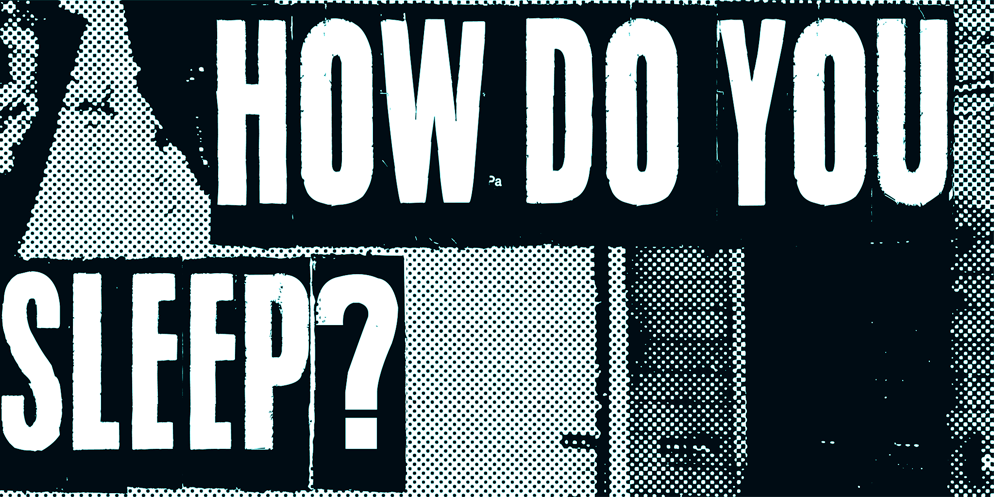
A How do you sleep? Font é uma elegante tipografia francesa para uso pessoal gratuita. Ela foi criada pelo designer Hamilton, conhecido por seus desenhos delicados e versáteis. Esta fonte tem um tom aconchegante e envolvente que se adapta perfeitamente para projetos decorativos, como decoração de livros, adesivos e até mesmo rótulos de doces. Se você deseja usar uma das minhas fontes em seu projeto comercial, basta entrar em contato. Você pode fazer um pagamento de 15€ (ou equivalente em outras moedas) por meio do PayPal para comprar a licença comercial. Após receber o pagamento, envie-me um email e eu ficarei feliz em fornecer a licensa. A How do you sleep? Font não é apenas uma fonte bonita; ela também tem uma propriedade única que se assemelha à tranquilidade da noite e ao conforto de um bom descanso, sendo perfeita para projetos relaxantes ou tranquilizadores. Regularmente, também estamos abertos a doações para ajudar-nos a manter nossa fonte gratuita, então considere fazer uma contribuição se achar que vale a pena. Essa font é perfeitamente adequada para criações decorativas e pode adicionar um toque único ao seu projeto, seja você criando um livro de contos fantásticos ou simplesmente adicionando um toque especial em seus rótulos de doces.